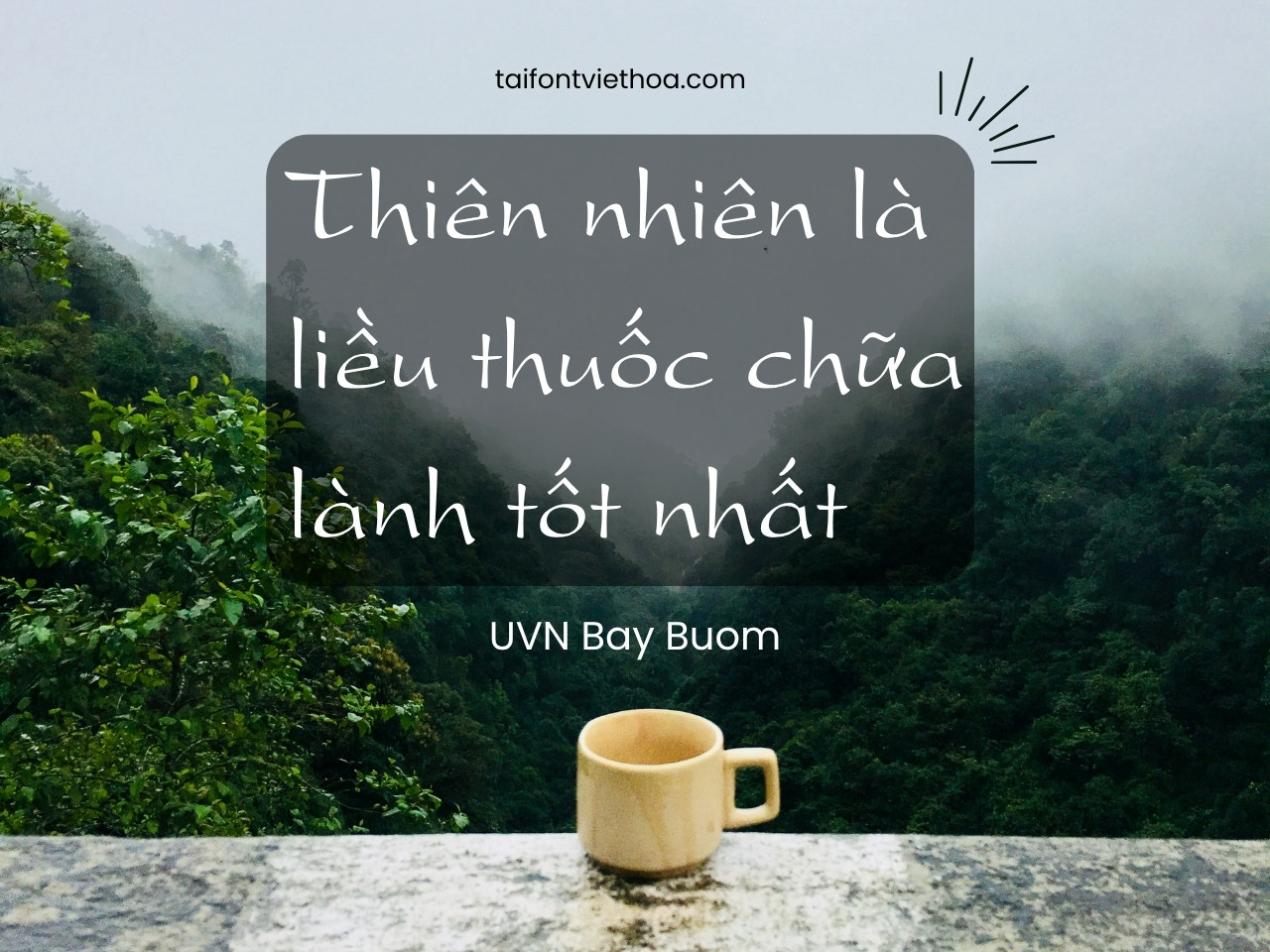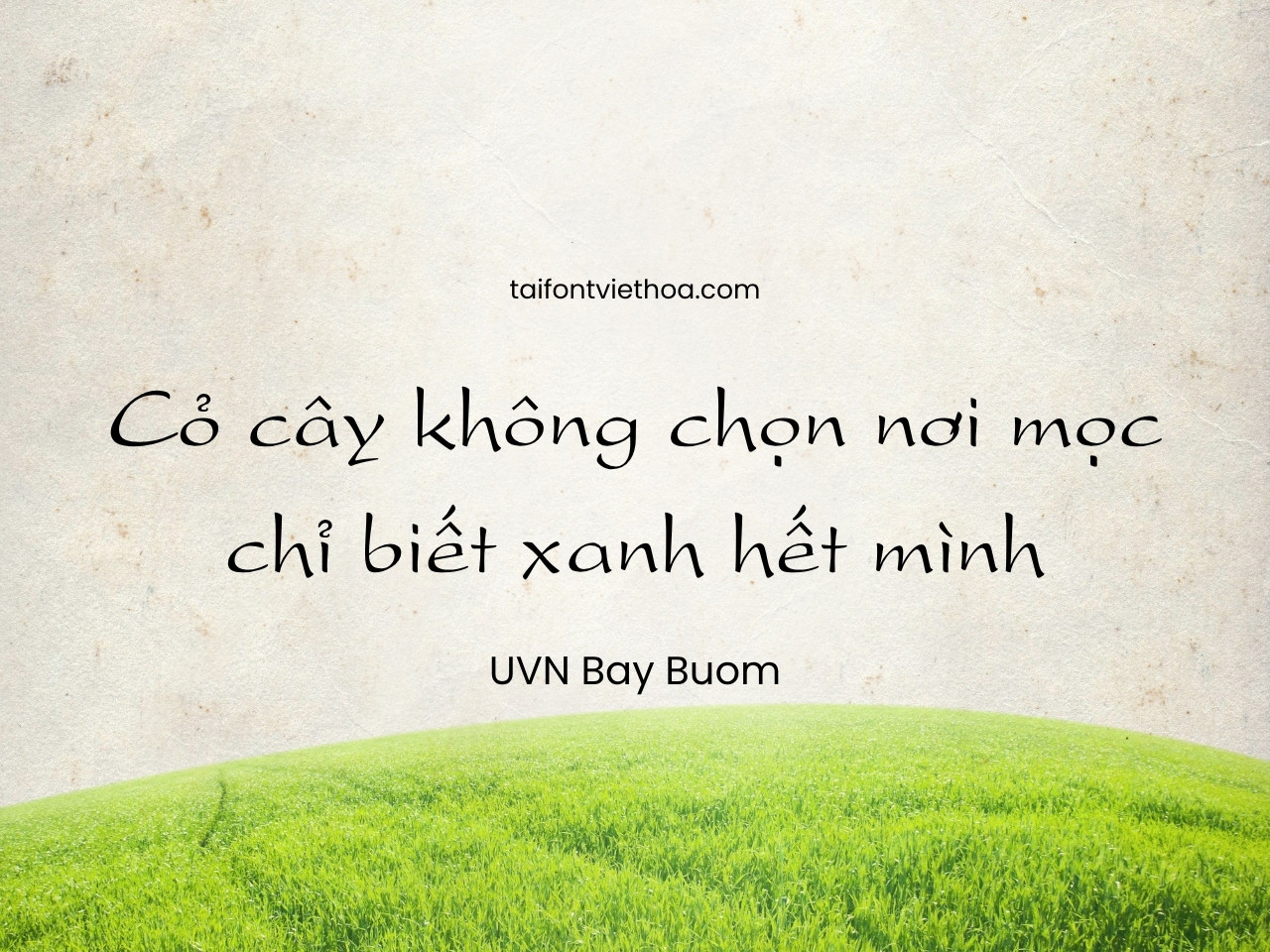
Font việt hóa UVN Bay Buom
Giới thiệu về font UVN Bay Buom
UVN Bay Buom là một font chữ viết tay đầy cảm xúc, lấy cảm hứng từ hình ảnh nhẹ nhàng và uyển chuyển của cánh bướm trong tự nhiên. Với nét vẽ mềm mại, uốn lượn và phóng khoáng, font mang lại cảm giác thơ mộng, sáng tạo và phù hợp với các thiết kế mang màu sắc nghệ thuật. Font này đã được sưu tầm và chia sẻ bởi thành viên Font Chuẩn, đồng thời được taifontviethoa.com chọn lọc và ứng dụng thực tế trong nhiều thiết kế thiệp mời, tiêu đề ấn phẩm và bao bì sáng tạo.
Đặc điểm thiết kế và ứng dụng của UVN Bay Buom
Font có dạng viết tay script, với các nét cong nhẹ, đường chuyển thanh đậm tinh tế và sự linh hoạt trong bố cục ký tự. Nhờ phong cách thiết kế bay bổng và đầy cảm xúc, UVN Bay Buom giúp tăng cường tính thẩm mỹ và sự mềm mại cho thiết kế tổng thể. Đây là lựa chọn tuyệt vời cho các ứng dụng cần sự nhẹ nhàng, sáng tạo hoặc mang thông điệp cá nhân hóa.
Font lý tưởng cho các thiết kế như: thiệp cưới, poster nghệ thuật, bao bì mỹ phẩm, logo thương hiệu nữ tính, thư mời, trích dẫn truyền cảm hứng. Ngành nghề phù hợp gồm: thời trang, mỹ phẩm, sự kiện cưới hỏi, thiết kế nội dung sáng tạo, quà tặng và đồ thủ công nghệ thuật.